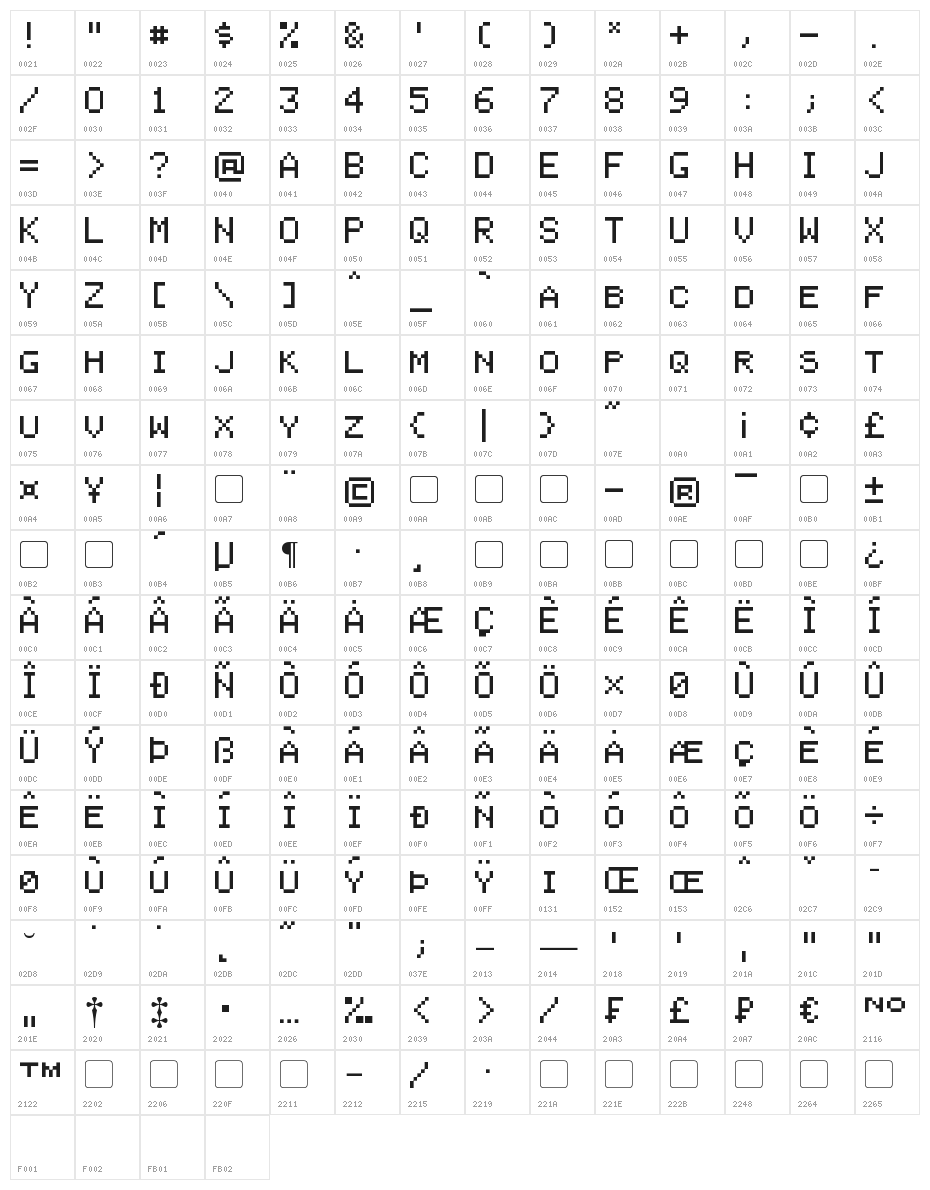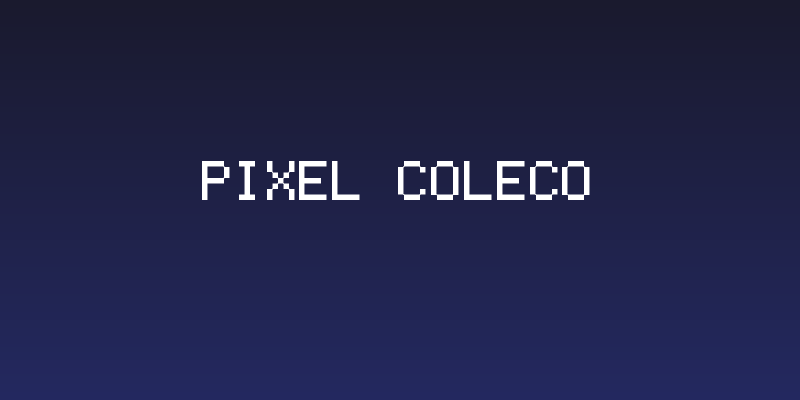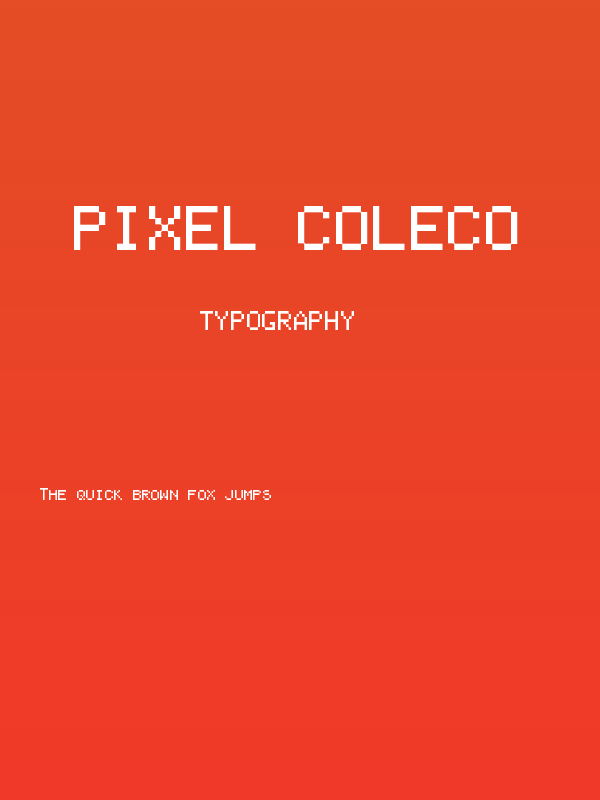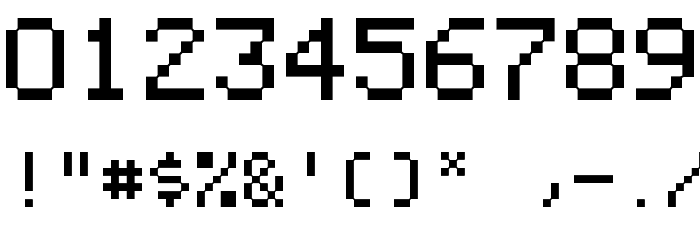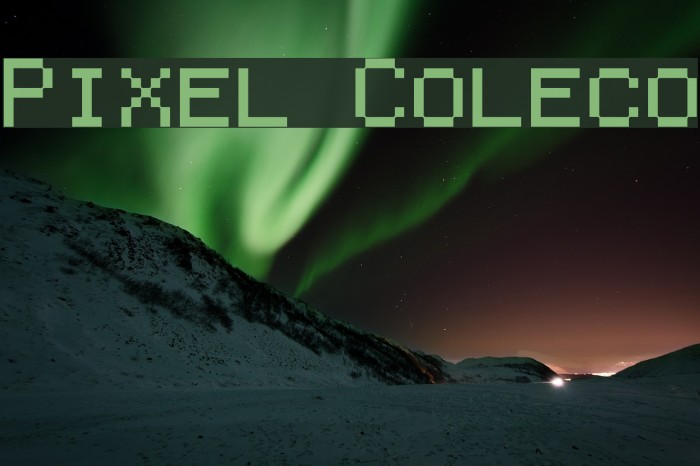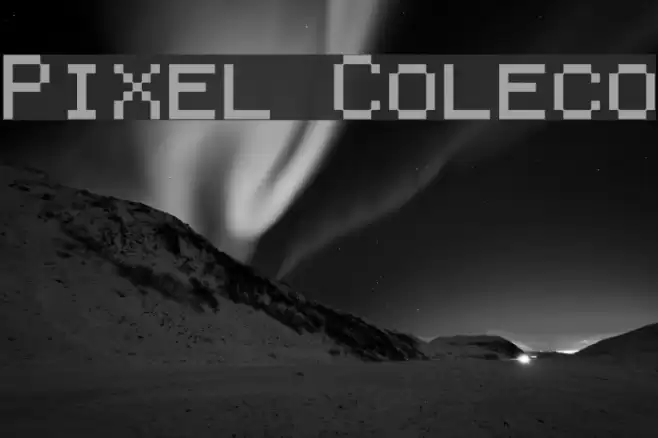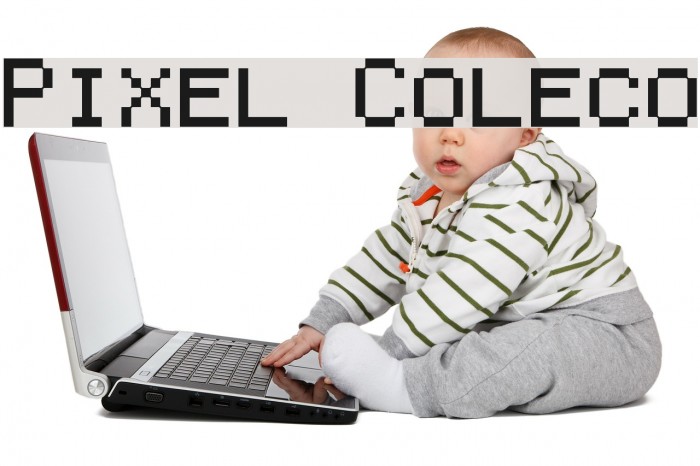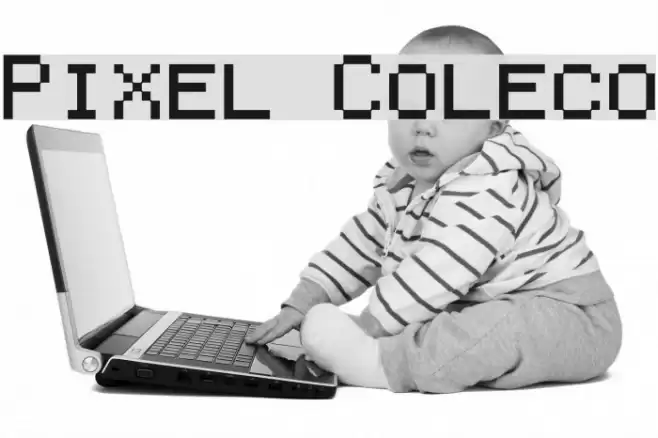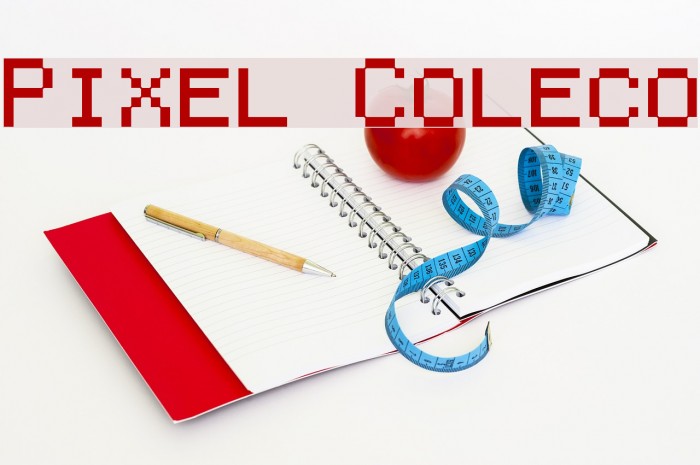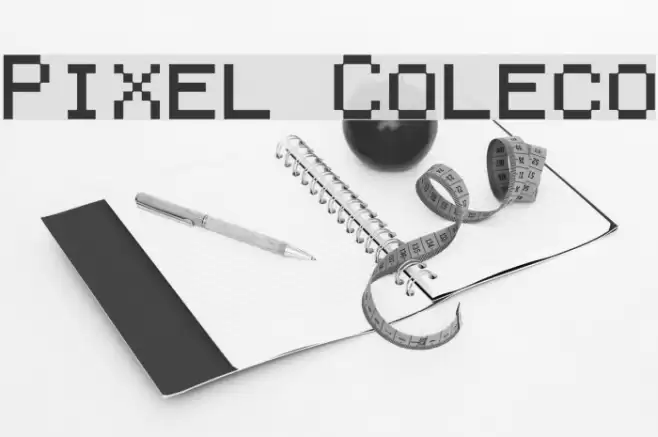
Pixel Coleco Font
| Gesamtstil | Retro, Digital |
| Anwendungsfall | Headlines, Logos, Digital Art |
| Vorgeschlagene Projekte | Ideal for retro video game designs, digital art projects, and any creative work seeking a nostalgic, 8-bit aesthetic. |